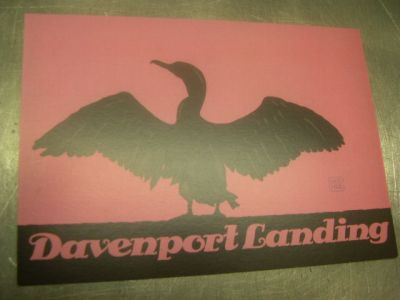
Moderne Illustrationen mit Schriften aus den 20er Jahren
Er kauft Bleisatz-Schriften aus den frühen 20er Jahren, läßt sich für seine Illustrationen, aus denen z.B. Schilder und Poster produziert werden, von Reklame-Vorlagen aus deutschen Bildbänden aus dieser Zeit inspirieren.
Heute hat er mir Postkarten seiner Arbeiten zur Kenntnisnahme zugesandt. Ich wollte sie eigentlich hier hochladen, habe aber dann gemerkt, daß sie auf seiner Webseite ebenfalls gezeigt werden in der Rubrik The Posters: http://www.stokessigns.com/viewportfolio.php?id=12
Was mir daran so gut gefällt, ist die Kombination aus diesen alten Schriften im heutigen modernen Umfeld. Der ganze Mann ist so. Man meint, mit einem dieser Beach Boys der 70er zu sprechen. Gleichzeitig ist er regelrecht besessen von seiner Arbeit als Illustrator.
Hier ein Bild:
Nicht alles, aber einiges davon wirklich sehr schön – nicht ganz so gut allerdings wie jene Amerikaner, die mit Holzlettern arbeiten und deren Name mir immer entfällt, den uns aber Dan Raynolds bestimmt gerne noch einmal in Erinnerung rufen wird …